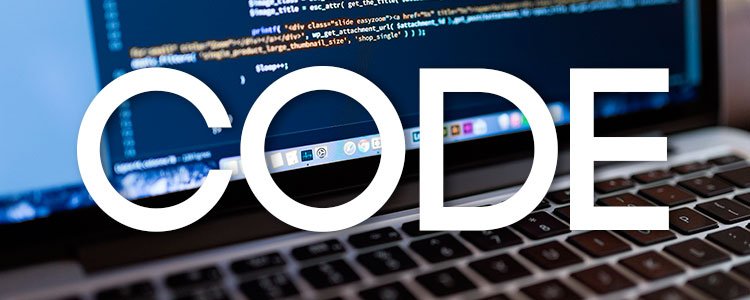
15 fantásticas fontes grandes e gratuitas
Se está a procura daquela fonte chamativa e de traços fortes para dar o devido destaque ao seu projeto, está no lugar certo.
Separamos 15 fontes gratuitas, que não economizam em seu tamanho. São fontes de diversos estilos e bem versáteis.
Gabo
Speakeasy
Coolvetica
KiloGram
Age
Gipsiero
WhoopAss
Alte Haas
Code
GreatLakes
Academic M54
Distant Galaxy
Chunk Five
MinstrelPoster
BP Diet